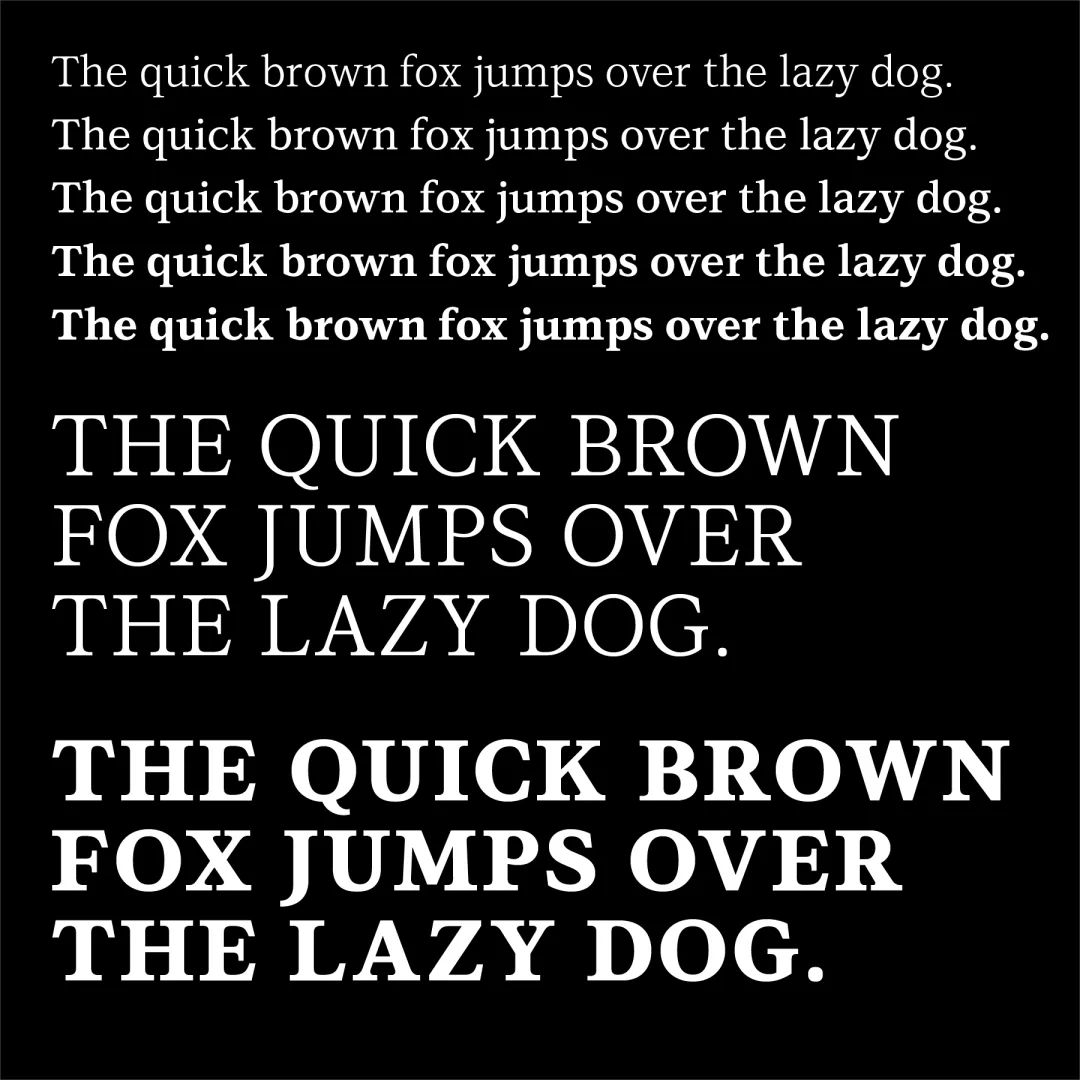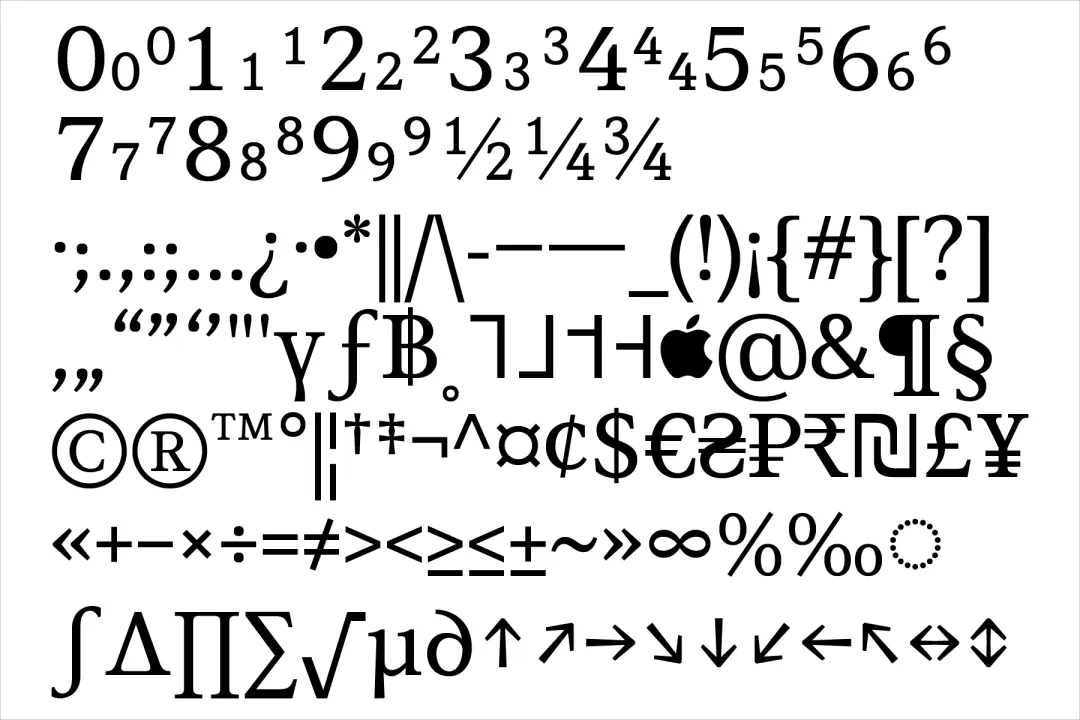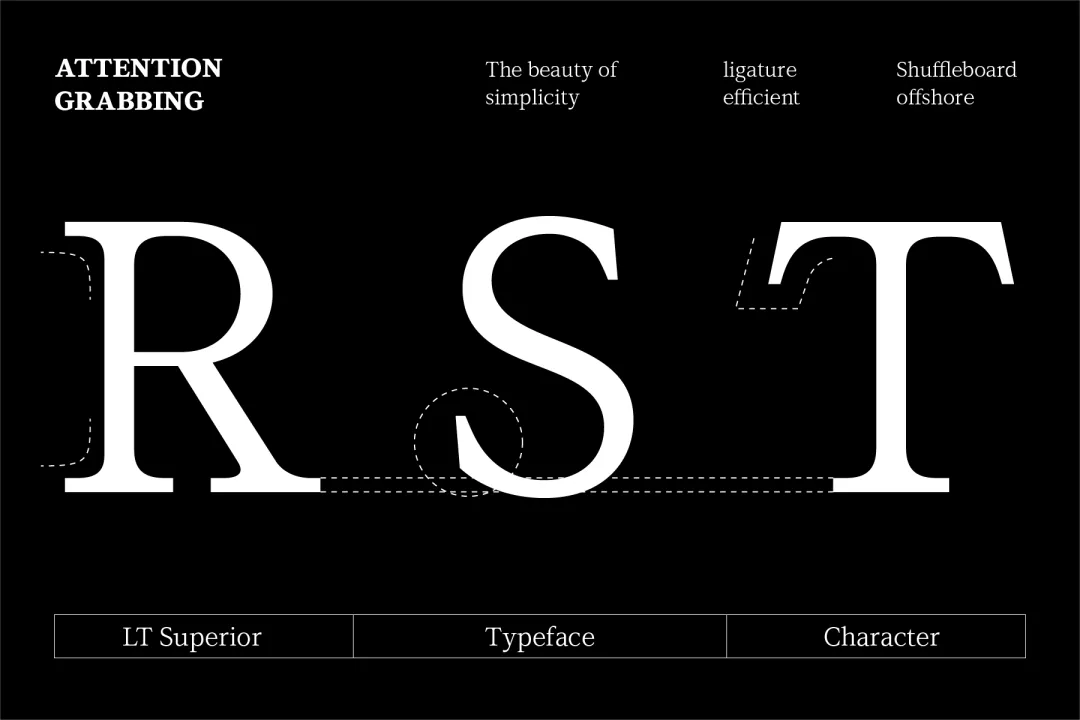
LT Superior Serif字体下载 高级免费商用英文衬线字体
LT Superior Serif 是 LyonsType 出品的免费衬线英文字体,字形简约精致、线条优雅,自带 Regular、Medium、Semibold、Bold、Extra Bold 多档字重,仅支持英文数字符号,OTF 格式,Win/Mac 通用。适合品牌标识、杂志排版、海报标题、高端包装等场景。
字体风格LT Superior Serif 出自 LyonsType,是一款现代衬线字体。小写字母偏高,字腔开阔,字号再小也清晰不糊;衬线短小简洁,不走华丽复古那一挂;笔画粗细反差温和,长文读下来不累眼。整体克制精致,理性里带着一点文学气。
适用场景它最适合需要气质的场合:独立杂志、艺术评论、诗集与小说封面;咖啡、文具、香氛这类强调质感的产品包装;画廊、书店、设计机构的品牌标准字。网页 UI 里做标题与正文混排,也能排出简约而不单调的层次。